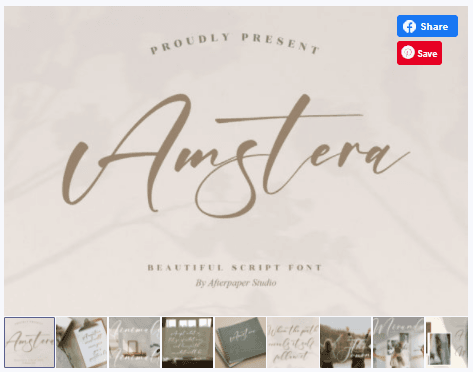
Amstera Beautiful Script Font
Amstera — это плавный рукописный шрифт. Влюбитесь в его восхитительный стиль и используйте его для создания роскошных свадебных приглашений, красивой стационарной графики, привлекательных постов в социальных сетях и многого другого!